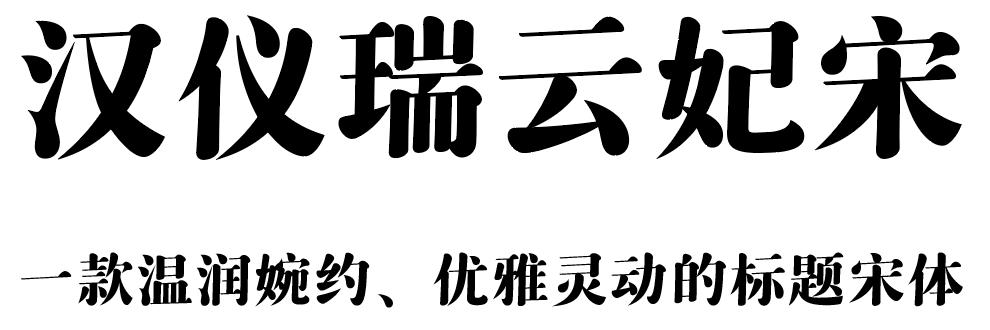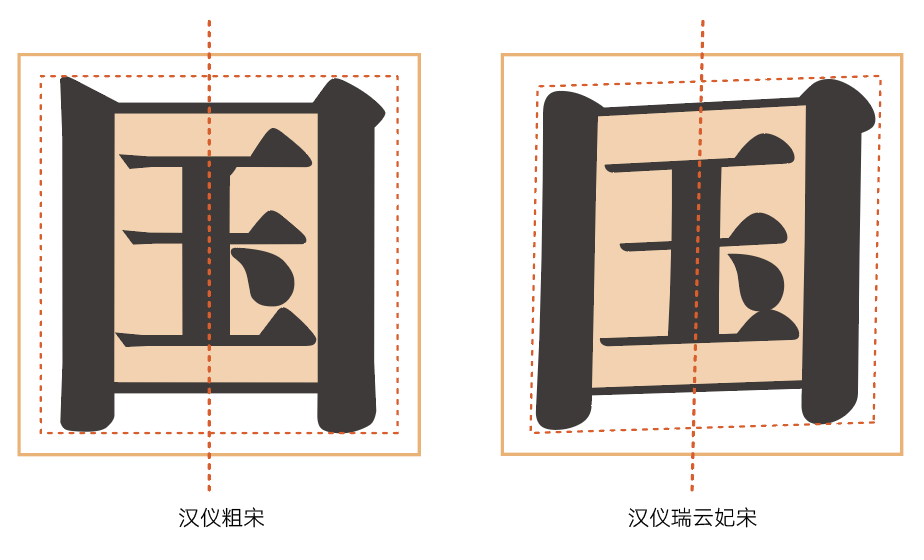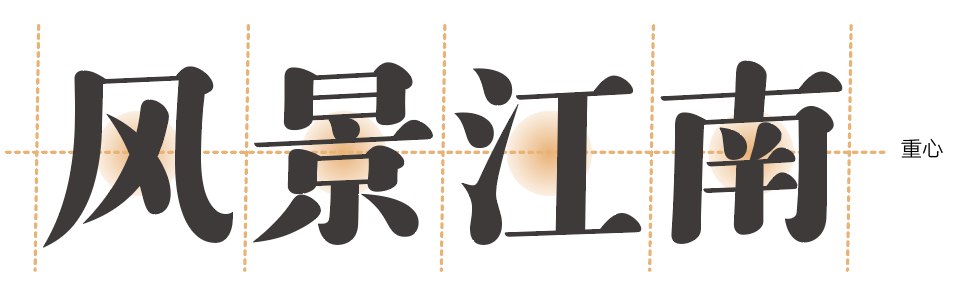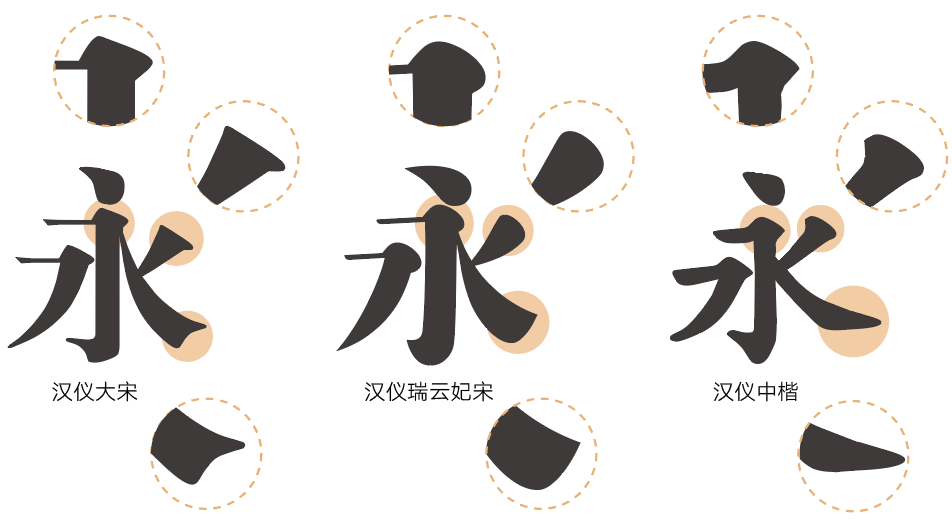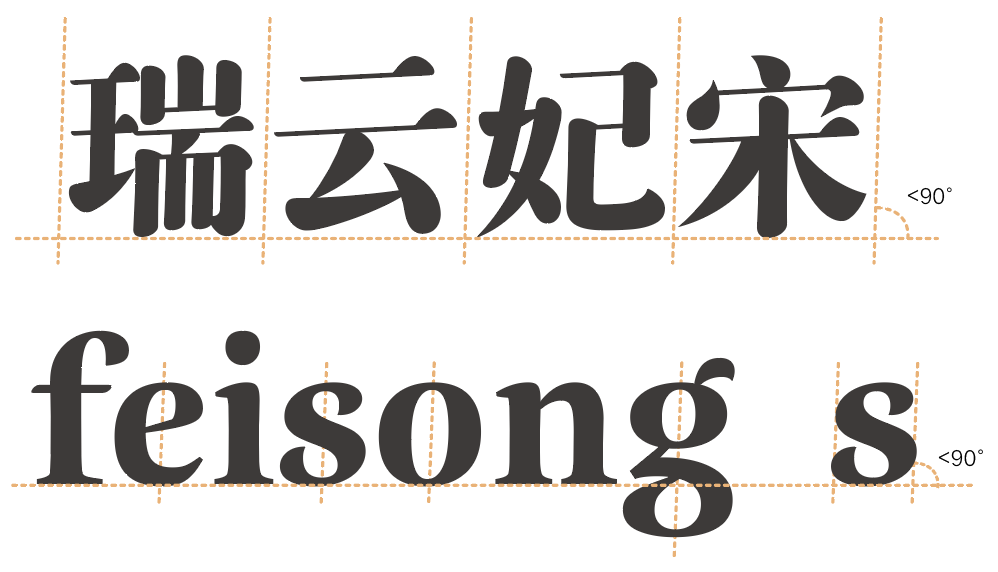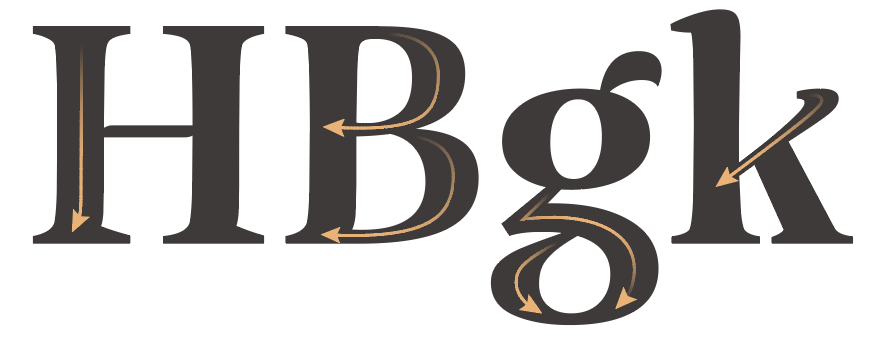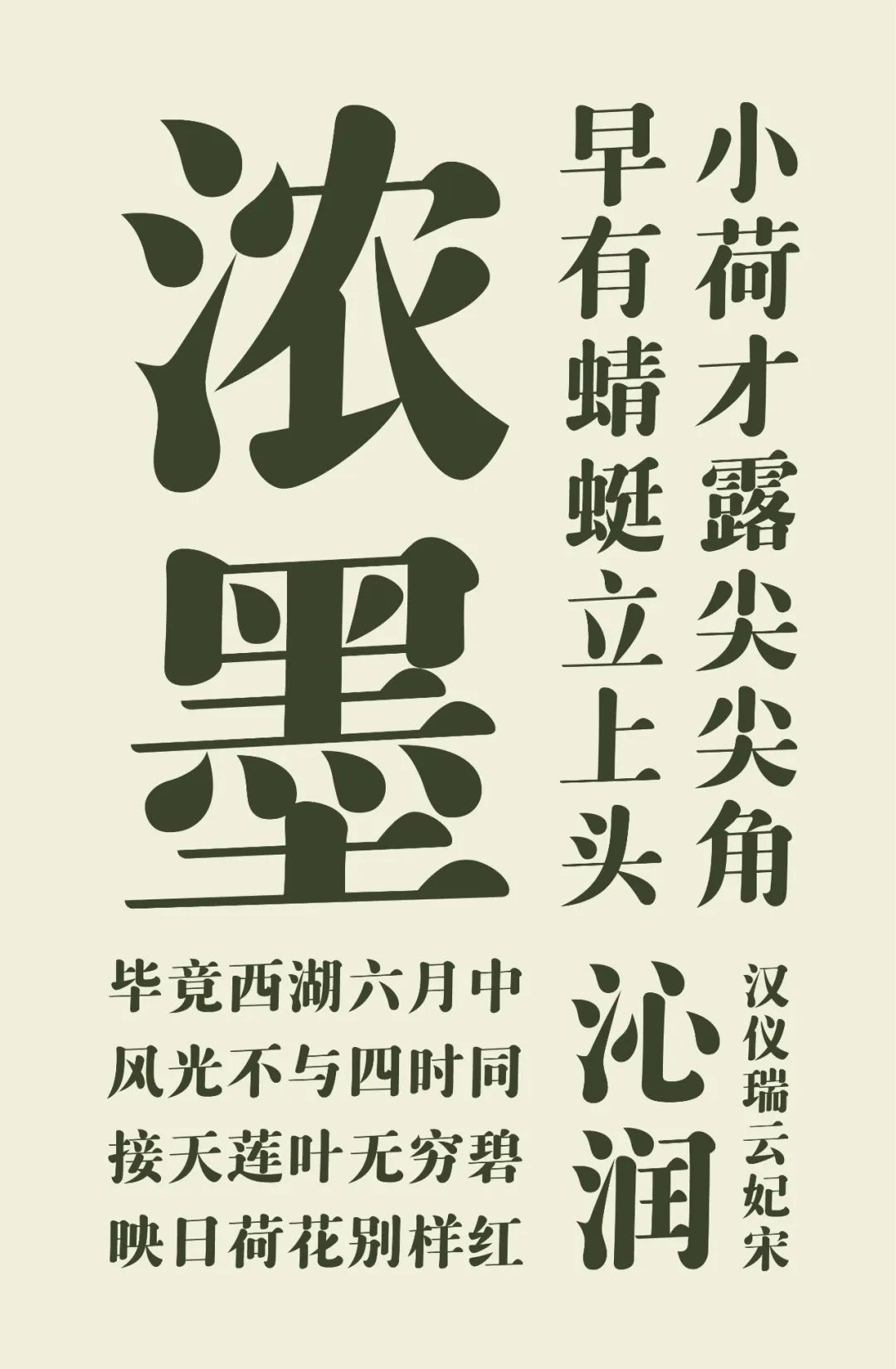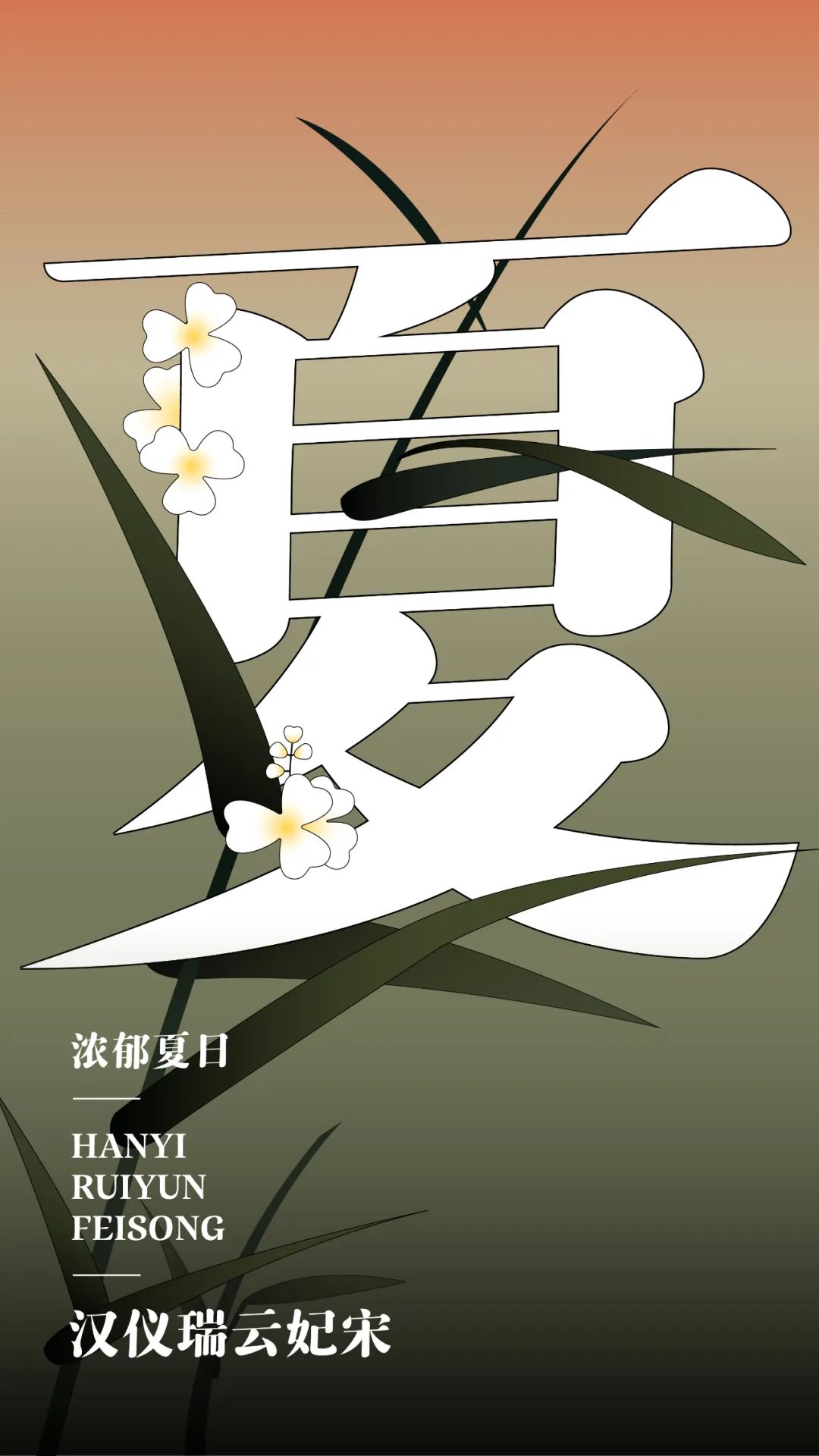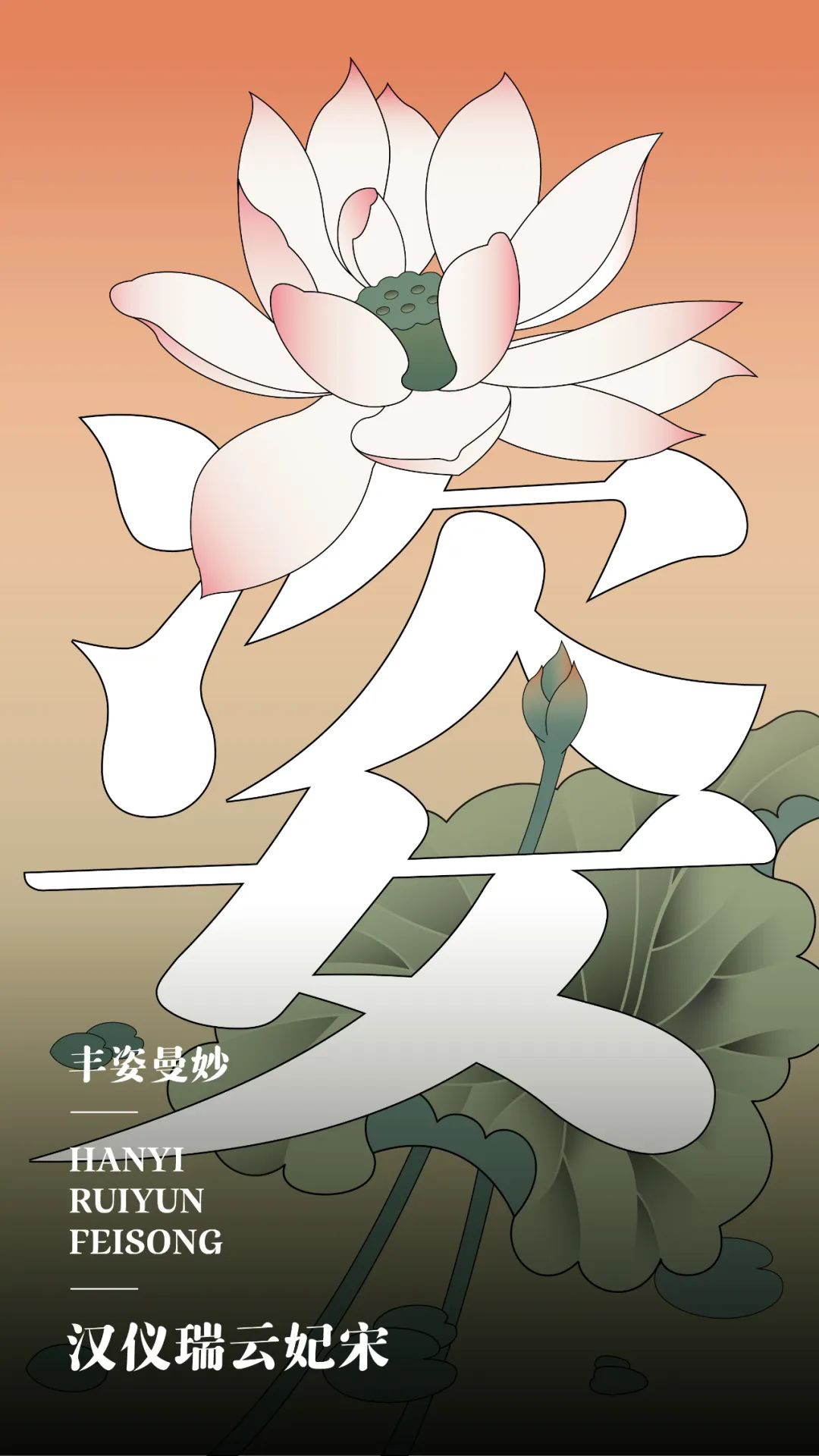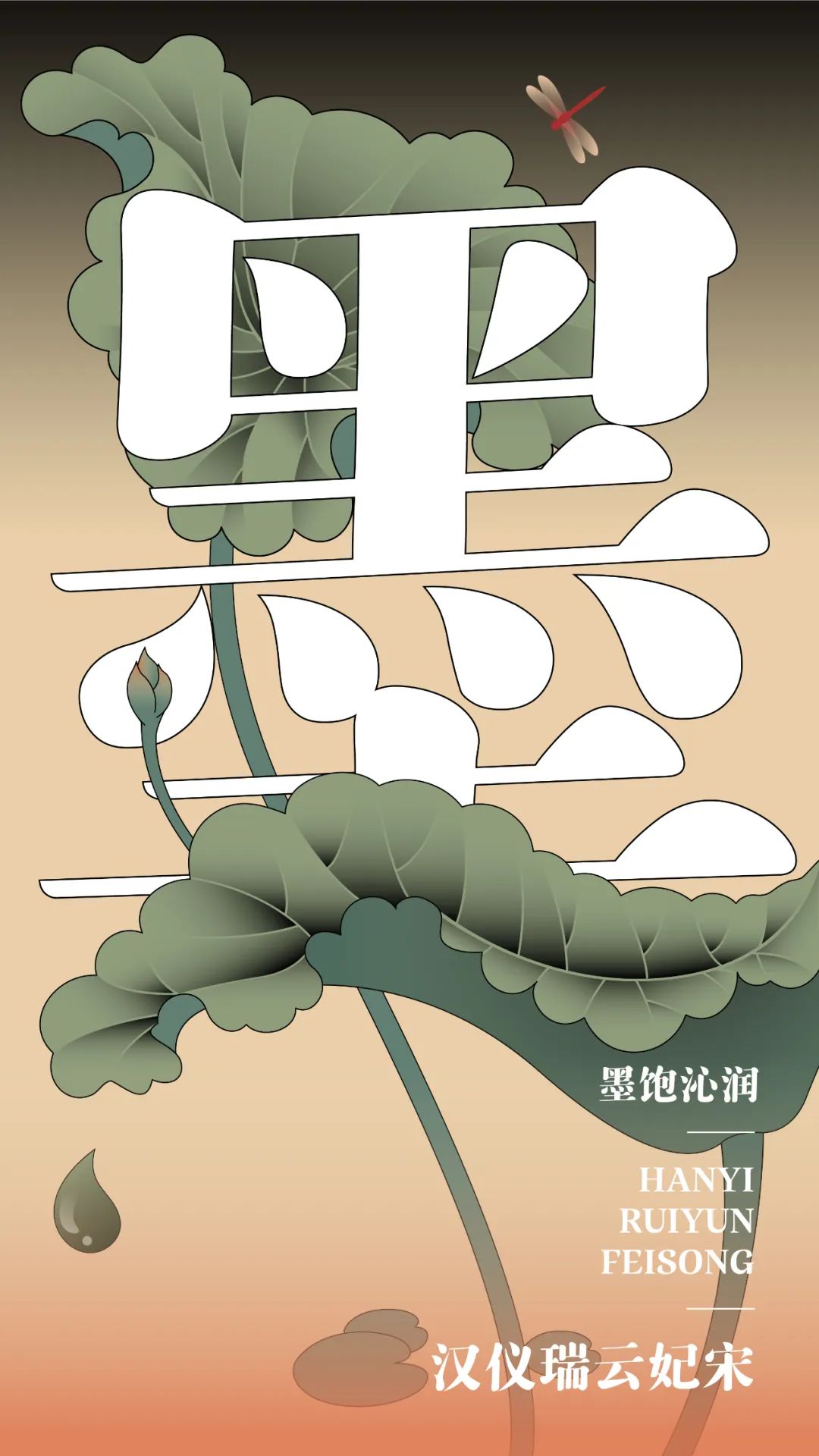
背景介绍
汉仪瑞云妃宋是汉仪字库签约设计师战国栋继“汉仪瑞意宋”、“汉仪瑞虎宋”之后主创的第三套字库。虽然都属于宋体字,但每款字体的性格形象还是非常不同的。如果说汉仪瑞意宋是现代时尚、冷酷高雅的商业人士的话;那么汉仪瑞虎宋就是虎啸风生、沉稳厚重,有着强大气势的猛男;而汉仪瑞云妃宋则是体态丰腴、婀娜多姿,漫步于西子湖畔的江南美人。
整体特点
汉仪瑞云妃宋是一款温润婉约,优雅灵动,带有人文特质的标题宋体。浓郁饱满的字型结构与传统严谨的宋体结构相结合,为这款字营造出一种诗情画意的表达环境,适合在浪漫的、温暖的、有情调的设计场景中使用。
结构自然倾斜
汉仪瑞云妃宋的字体结构与常规宋体不同,它的字面自然倾斜,带有书写气息。
汉仪瑞云妃宋的整体结构取右倾斜势,字面为不平行四边形,左右竖线及上下横线的倾角均不平行,右侧竖线和底部横线角度取向平缓,使得整体字形具有书写动感。
字形舒展放松
汉仪瑞云妃宋的字形斜中求稳,重心一致。字形舒展放松,布白均匀,整体和谐统一,传递出优雅稳重的感觉。
汉仪瑞云妃宋的笔画特点与常规宋体相仿,但弱化了常规宋体的笔画刀刻感强调书写性,相对常规宋体的工业感而言,汉仪瑞云妃宋笔墨浓重,概括写意,形态丰腴灵动,具有人文气息。
笔画丰润饱满
汉仪瑞云妃宋横笔画均有向右上倾斜的书写之势,笔画造型丰润饱满。
竖画的起笔、收笔造型概括了常规宋体的笔锋顿挫,更加简洁柔和。
勾、撇、捺、点这类动态笔画,概括了宋体特征,造型如水滴一般饱满,曲线变化丰富,优雅灵动,又富有力量。
中西文匹配
汉仪瑞云妃宋的西文有着微微右倾的stress angle(中轴线),与中文向右倾斜的视觉感觉相配,使竖直字形的西文也能有右倾的视觉感。
汉仪瑞云妃宋的西文在常规衬线体中加入了一些书写特点,以呼应中文的特性,也增添出一些趣味。
排版效果